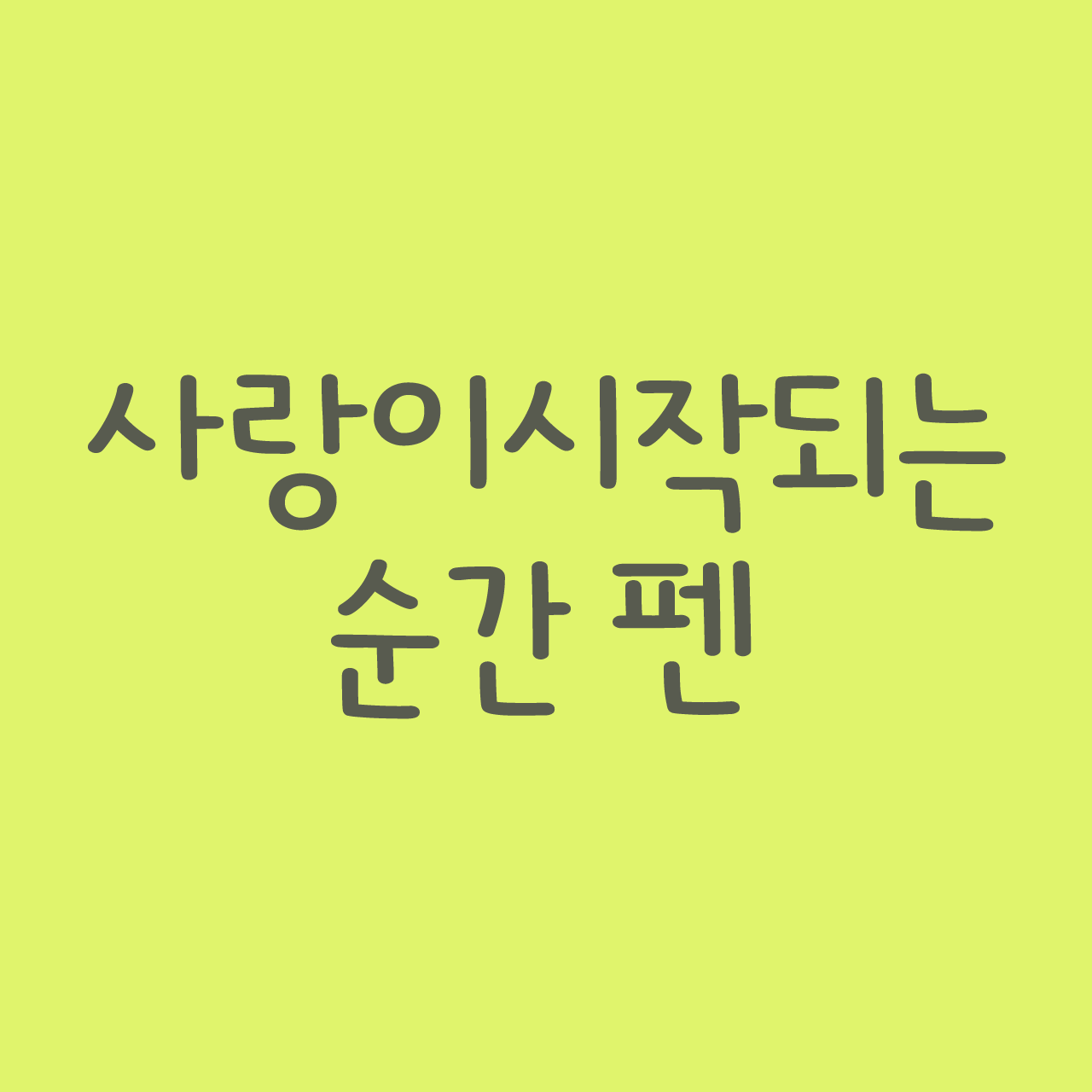
And사랑이시작되는순간 펜
About "And사랑이시작되는순간 펜"
‘And사랑이시작되는순간 펜’은 ‘And사랑이시작되는순간’을 바탕으로 제작되었습니다.
납작 펜으로 쓴 것처럼 가로 획이 세로 획보다 얇은 서체로, 다이어리에 쓴 듯한 아기자기한 손글씨의 느낌을 가집니다.
제목용으로 쓰임이 좋은 'Regular, Medium, Bold, ExtraBold' 총 4가지 굵기로 구성했습니다.